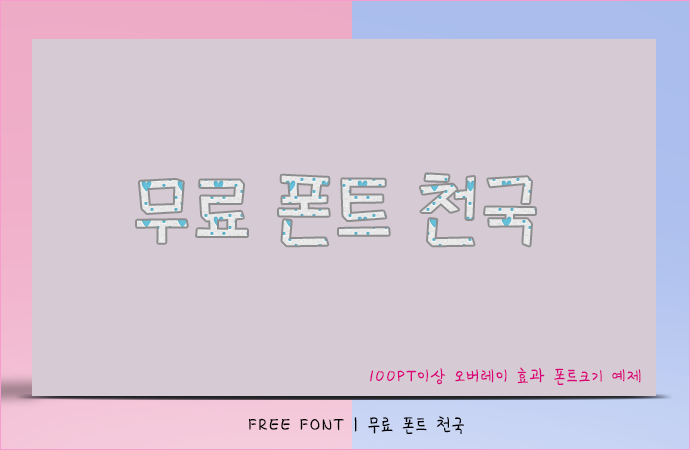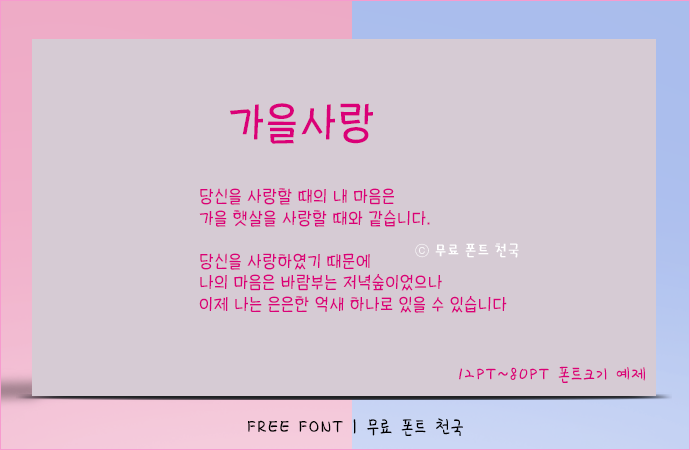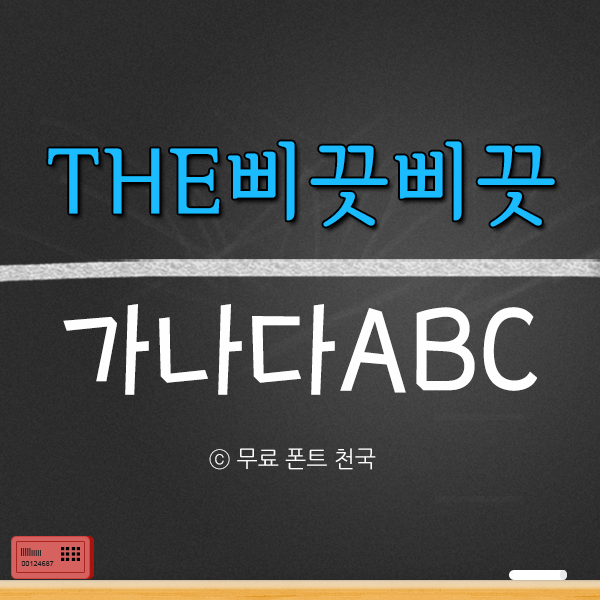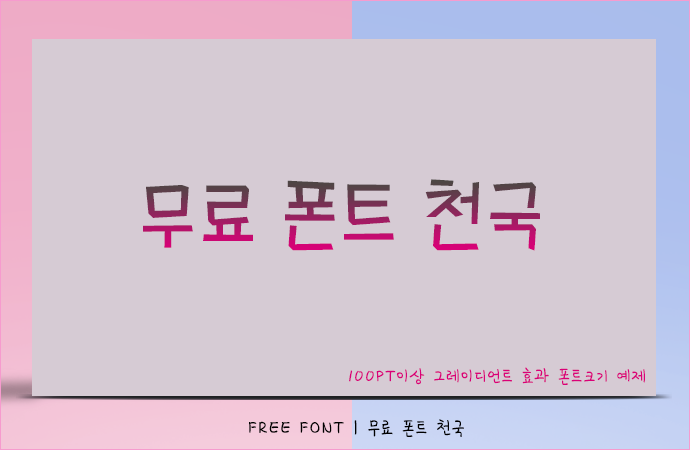
삐뚤 삐뚤 개성있는 THE삐끗삐끗 한글폰트
THE삐끗삐끗 폰트 정보
날카로운 직선과 약간 기울어진 효과가 적용된 'THE삐끗삐끗' 서체입니다. 돋움체와 굴림체처럼 딱딱한 느낌에서 탈피해 좀더 친근감 있게 제작되었습니다. THE삐끗삐끗 폰트는 개인적인 용도로 사용할 수 있는 제한적 무료 버전입니다. 단체나 공공기관 등에서 사용을 원할경우 아래 링크된 사이트에서 개별 폰트를 구매하셔서 사용하시길 바랍니다.
THE삐끗삐끗 폰트 # 미리보기
THE삐끗삐끗 폰트, 12~80PT 크기로 적용한 효과
THE삐끗삐끗 폰트, 100PT 크기 이상으로 작업한 오버레이 효과
THE삐끗삐끗 폰트, 100PT 크기 이상으로 작업한 그레이언트 효과